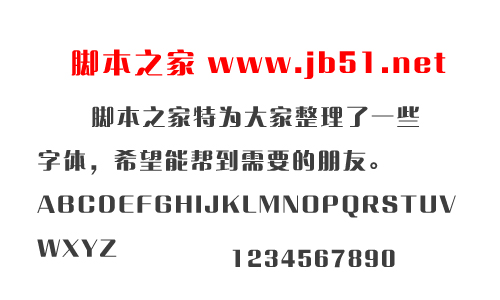
方正清純體簡體 Heavy字體(FZQingChunTiS Heavy.otf)是方正清純體系列中字重最高的方正清純體_特字體,該字體橫細(xì)豎粗,筆形富于變化,整體給人清新、靈動(dòng)、優(yōu)美、圓潤之感,且字體庫完整,可以廣泛應(yīng)用于橫幅標(biāo)語、美術(shù)設(shè)計(jì)、宣傳海報(bào)、ppt、影視制作以及內(nèi)容用字等領(lǐng)域,歡迎有需要的朋友前來下載使用,